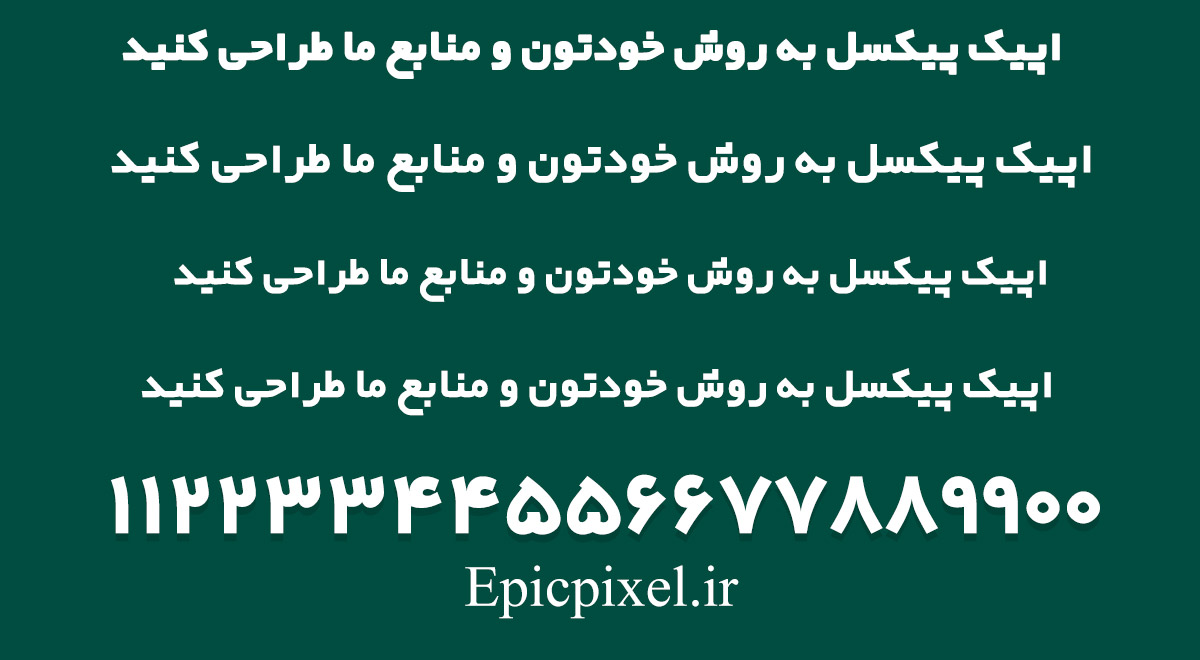
3 فونت یکان پلاس فارسی
دانلود مجموعه کامل فونت Yekan Plus فارسی Font یکان پلاس رایگانفونت یکان که ظاهر رسمی و جدی داره ، یکان پلاس هم یک نسخه ارتقا یافته از فونت رسمی یکان هست که کمی توی گراف و ظاهر فونت تغییر ایجاد و اصلاح شده بعلاوه نقطه های فونت که بصورت بهم چسبیده و خاص طراحی شدن |